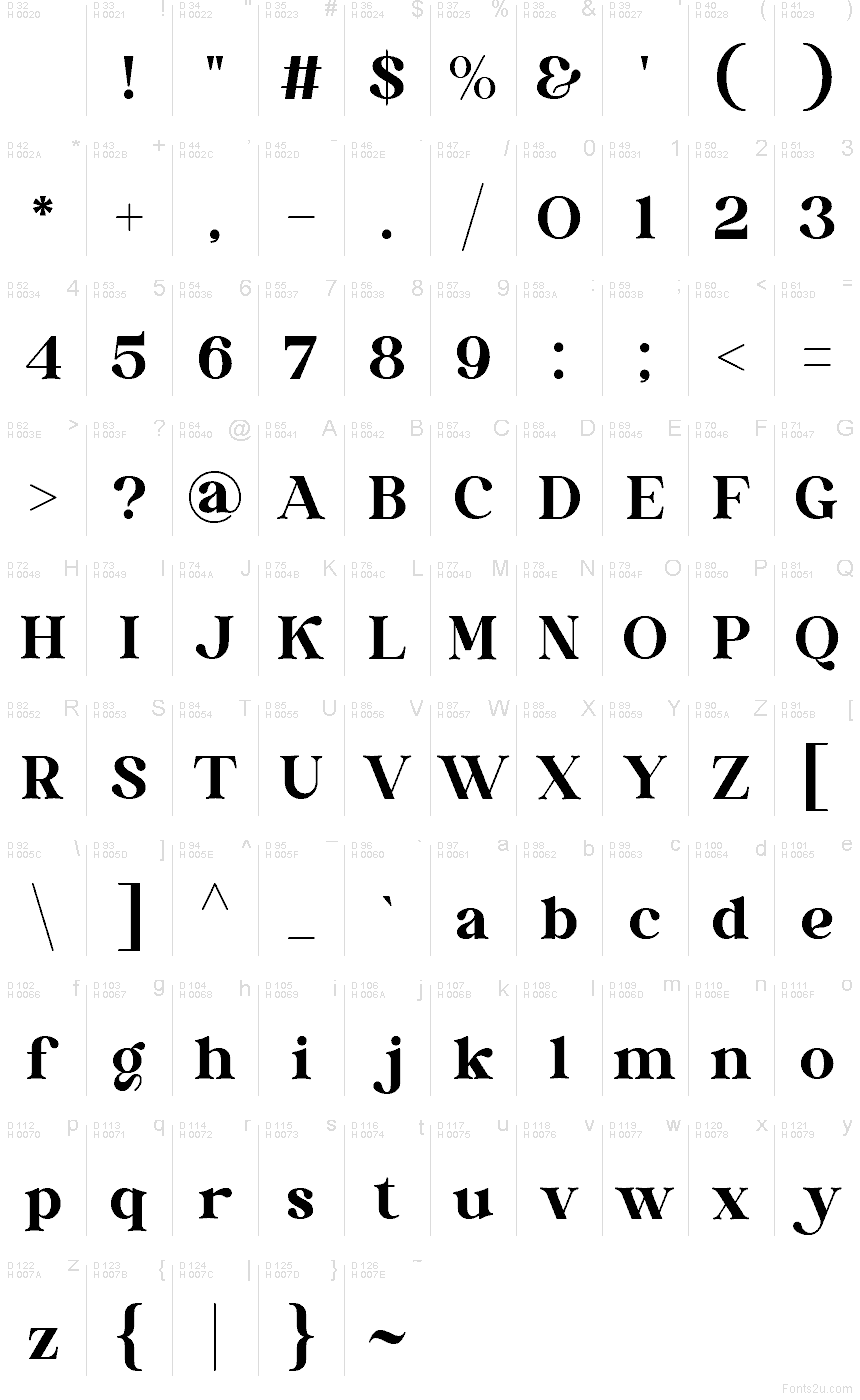
Desenvolvida pelo Ermedia Studio, a Grilan Acisen é uma fonte serifada gratuita e de alto contraste, com o porte formal de uma didona moderna. Suas formas esguias terminam em serifas finas e de corte preciso.
Os cabeçalhos de revistas de moda constituem seu uso mais evidente, unindo variações marcantes de espessura a uma elegante voz editorial. Essa mesma precisão atende perfeitamente a embalagens de cosméticos e cartazes de eventos culturais, contextos nos quais a tipografia evoca refinamento em vez de mero ornamento. Essas aplicações se unem pelas silhuetas nítidas e pela sobriedade formal da fonte.